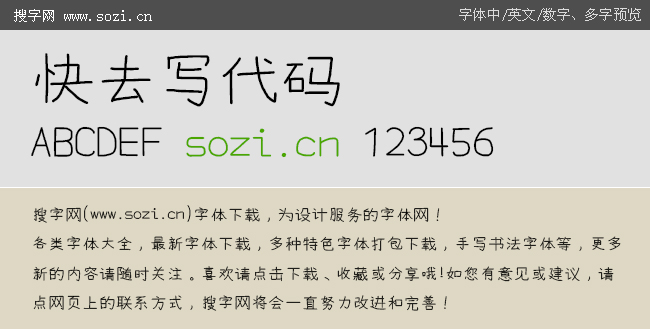
快去寫(xiě)代碼字體
搜字網(wǎng)給大家提供一款快去寫(xiě)代碼字體中文字體下載,快去寫(xiě)代碼字體是一款完全用鼠標(biāo)構(gòu)建字形的“仿”手寫(xiě)體,本字體最大的特點(diǎn)就是里面的絕大部分字形均由鼠標(biāo)繪制。適用于海報(bào)設(shè)計(jì)、包裝設(shè)計(jì)、廣告設(shè)計(jì)等場(chǎng)景。